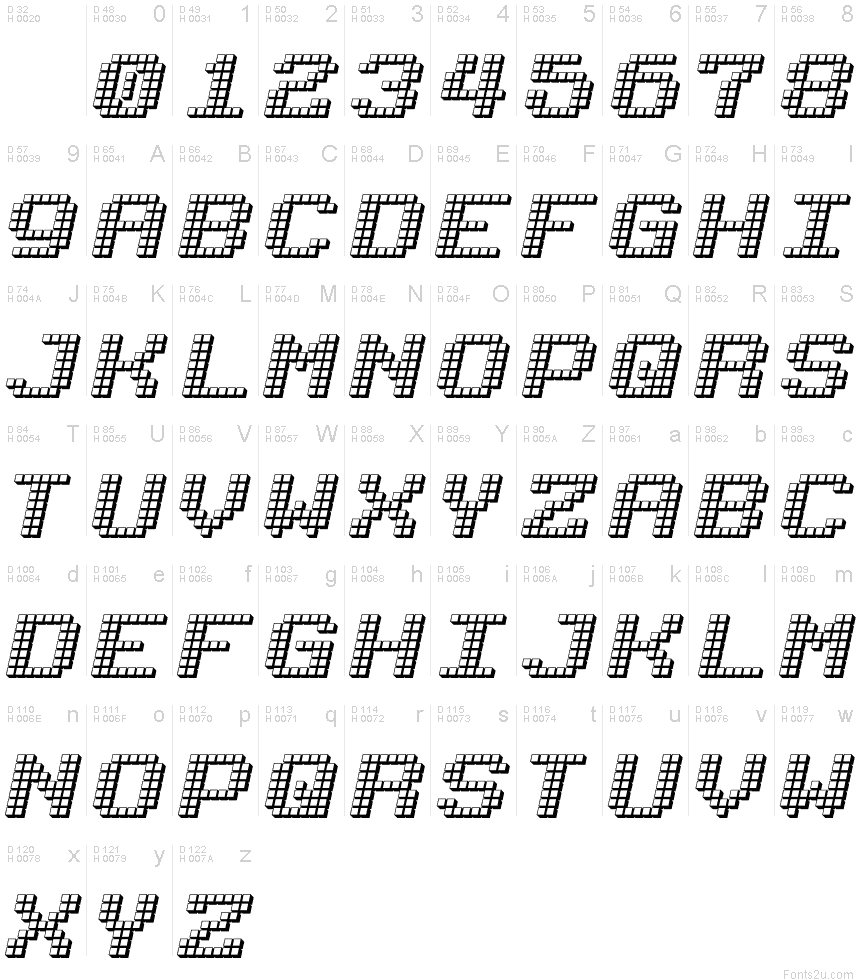
Lots of Dotz di Jakob Fischer è un font display digitale gratuito, composto da tessere rettangolari dagli angoli arrotondati che conferiscono a ogni lettera una costruzione segmentata, simile a quella di uno schermo. Gli spazi ripetuti tra i blocchi creano un ritmo modulare punteggiato, che appare più assemblato che disegnato.
Questo font gratuito è perfetto per titoli di poster, loghi in stile arcade, banner tecnologici, flyer di eventi e design di etichette brevi che richiedono un tocco elettronico o informatico. La sua struttura a blocchi è ideale anche per grafiche di giochi, promozioni di app e accenti editoriali dove un pattern geometrico digitale riesce a comunicare il messaggio senza bisogno di decorazioni extra.